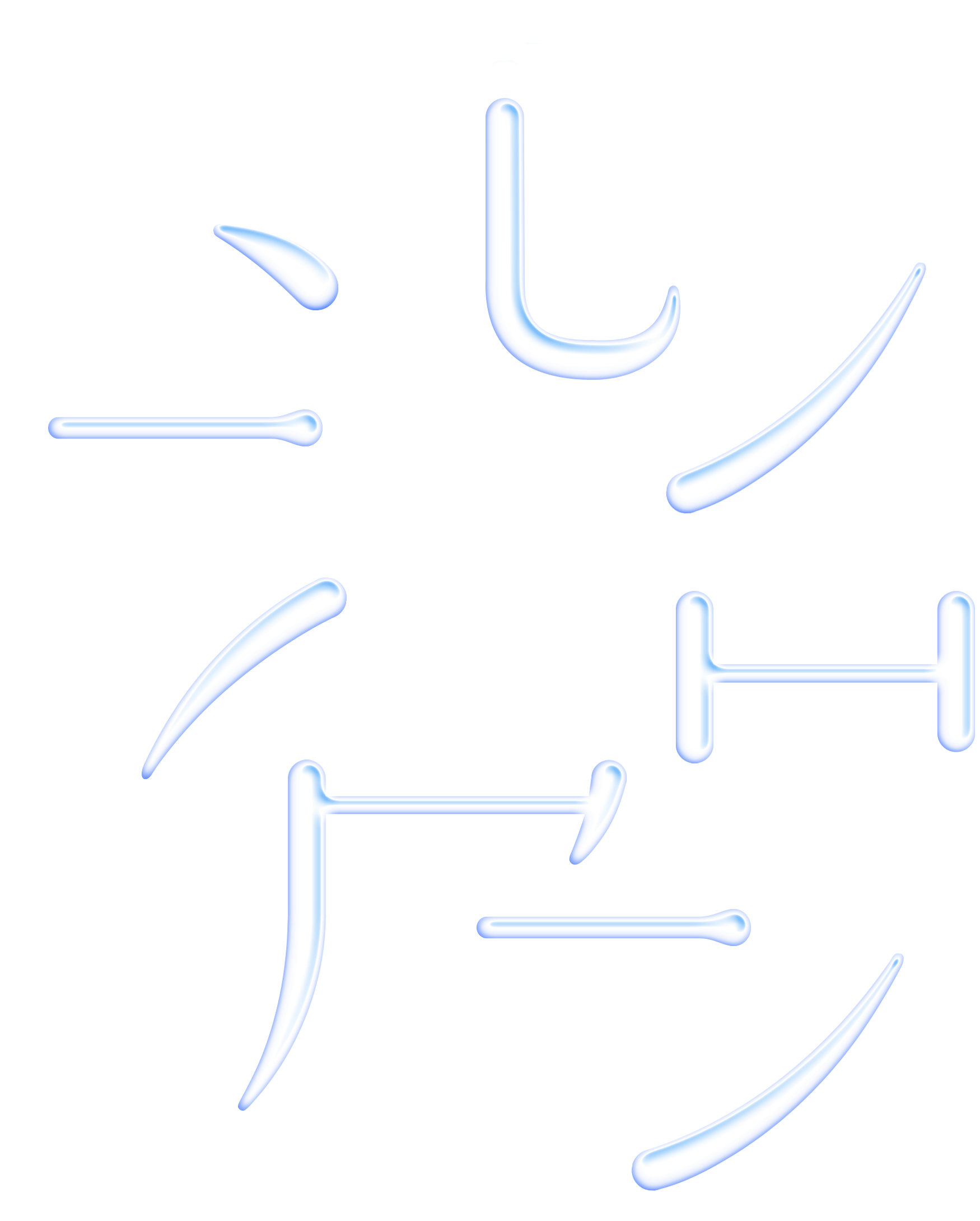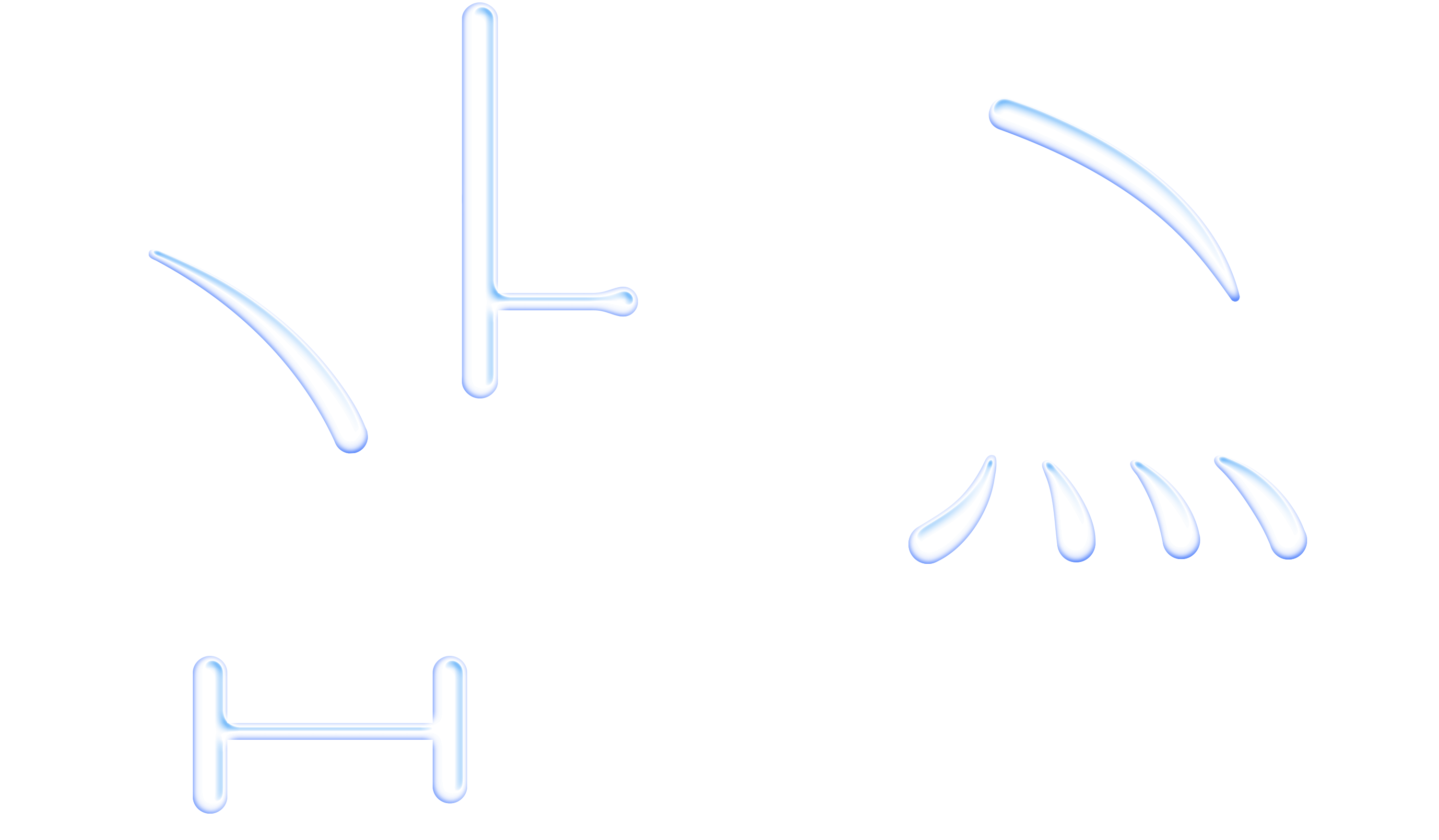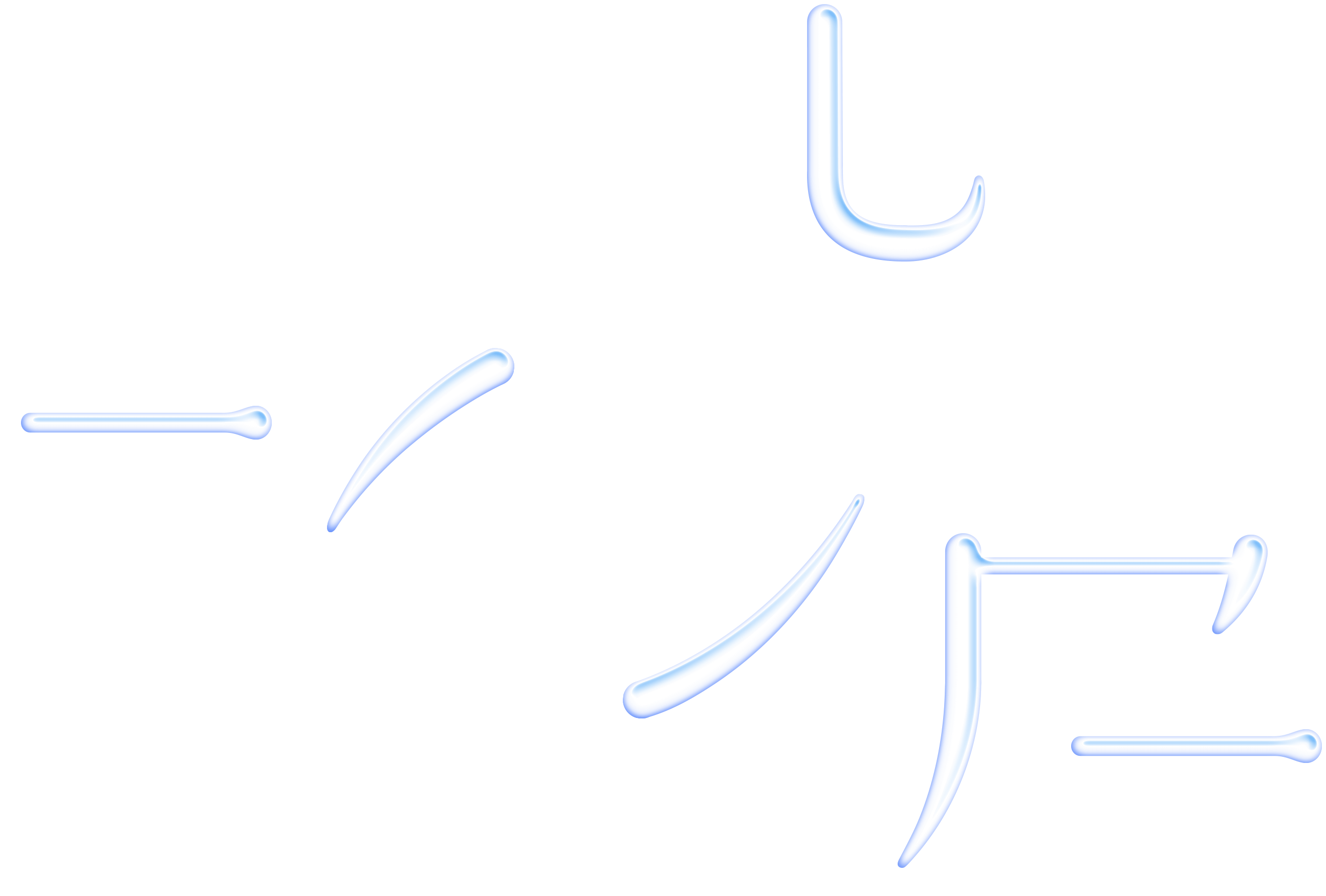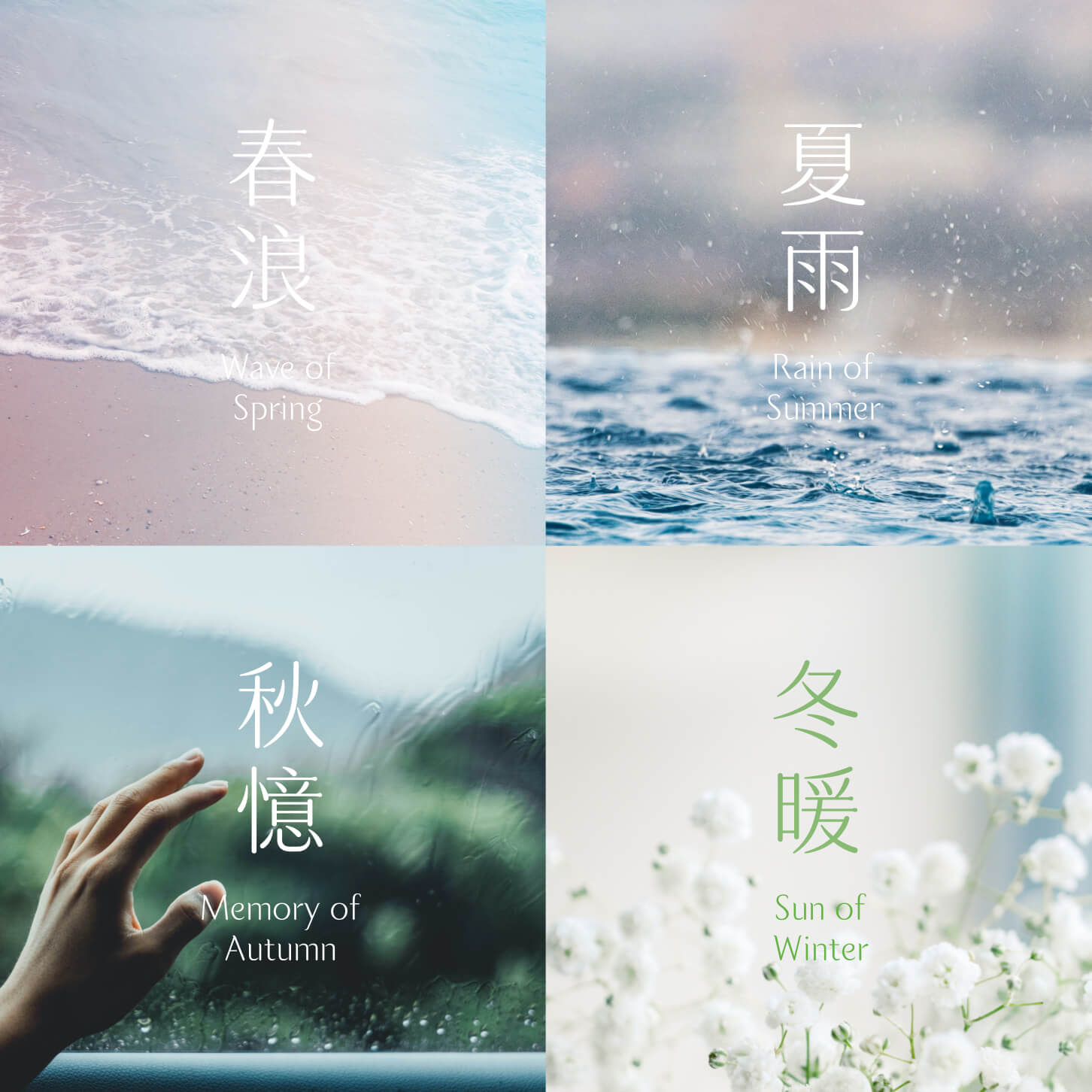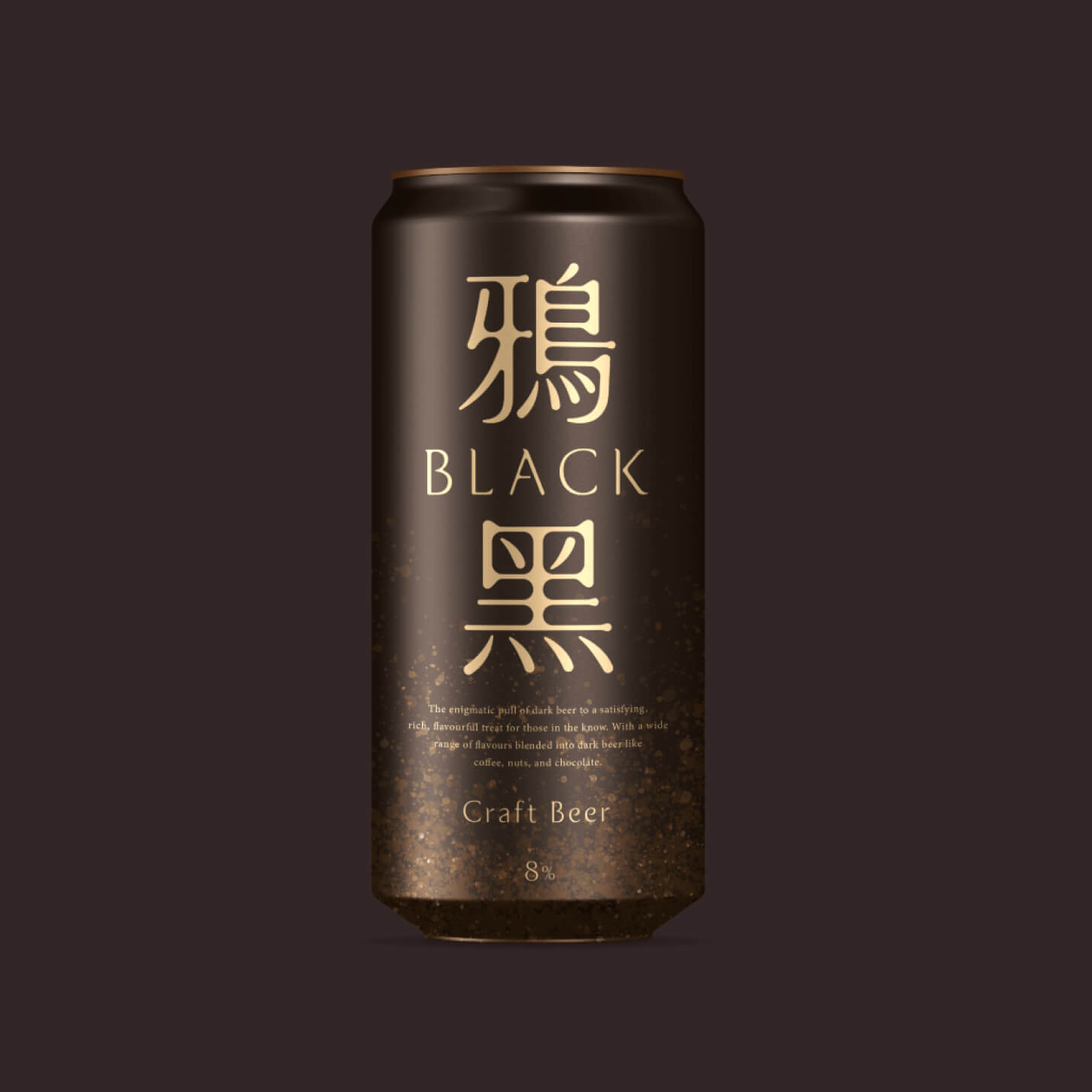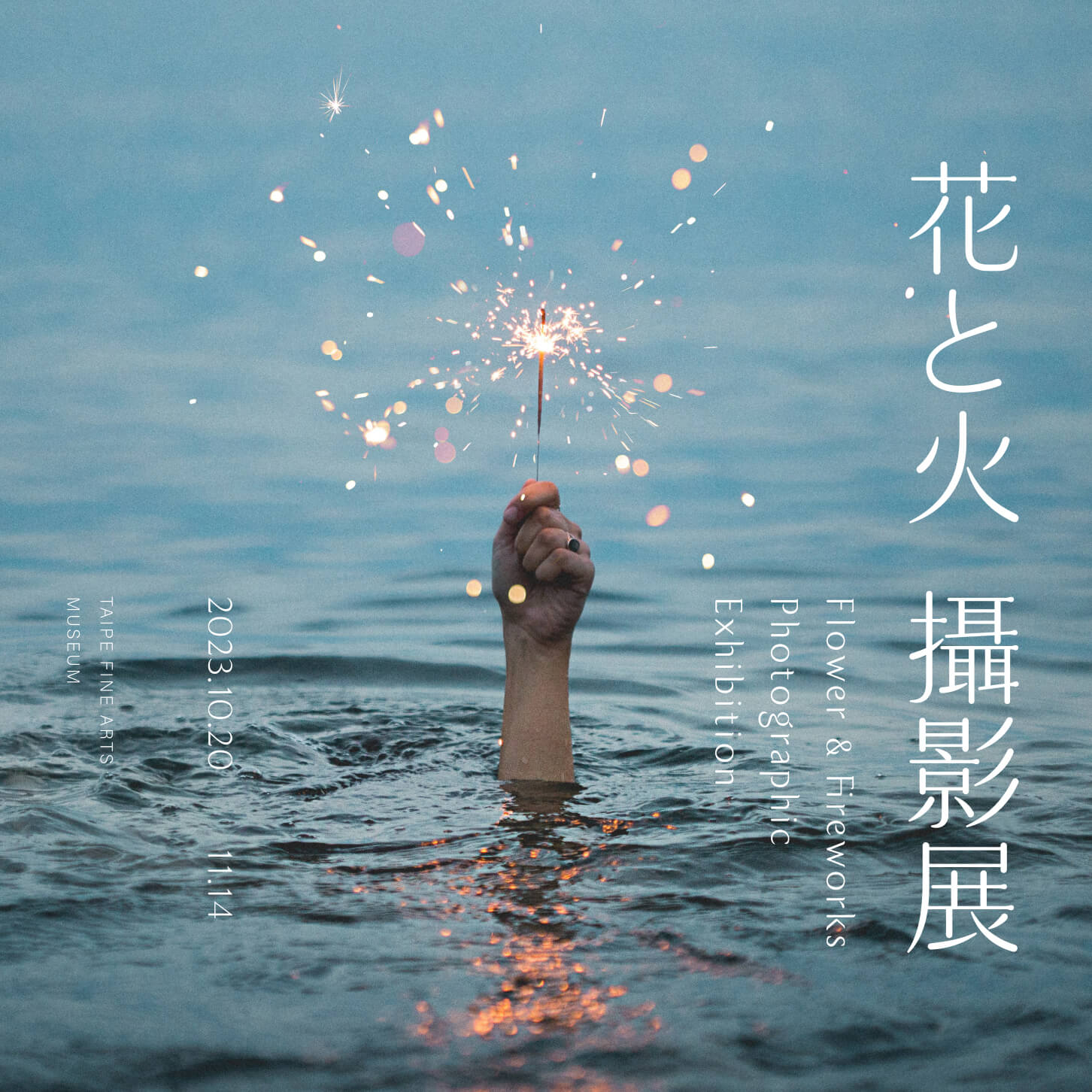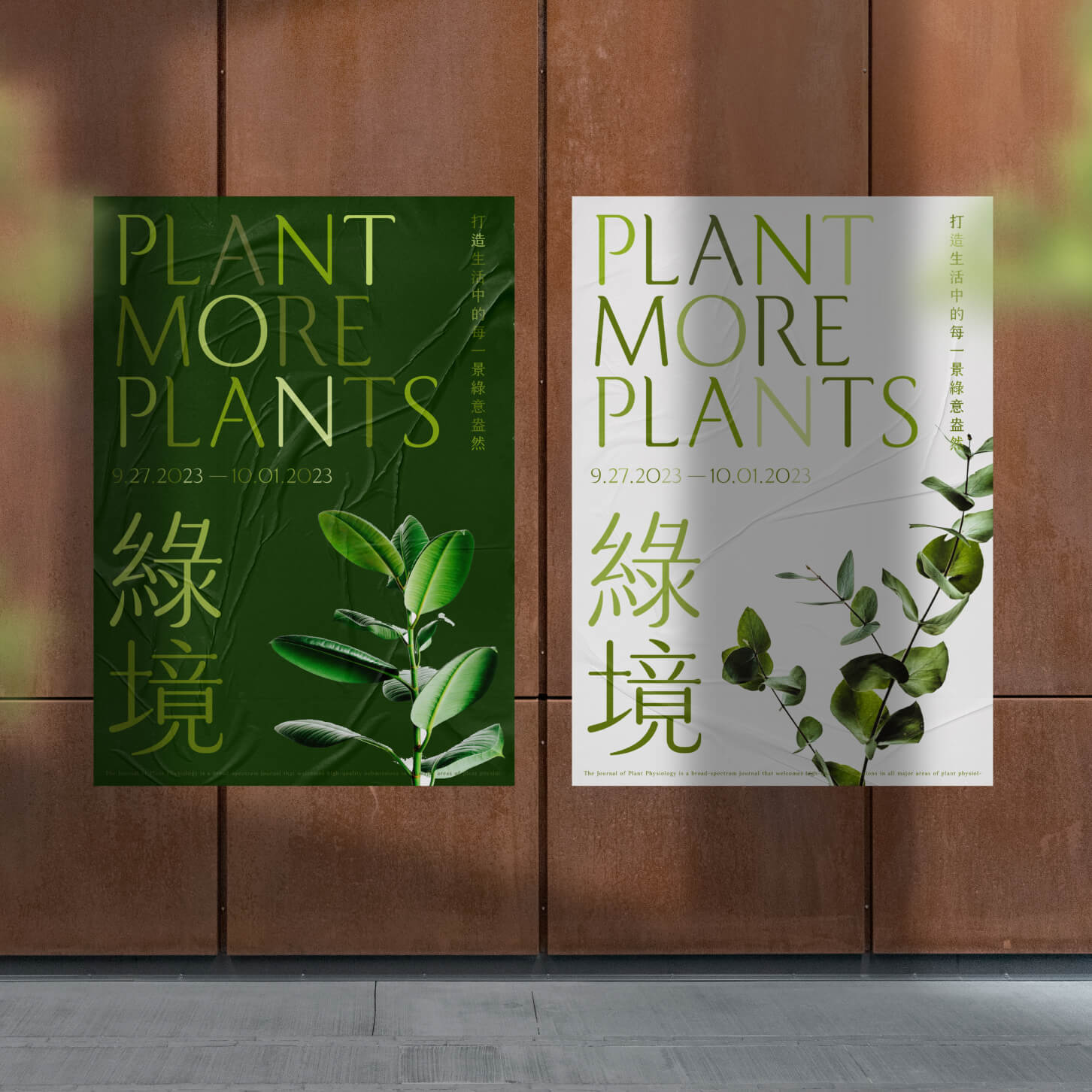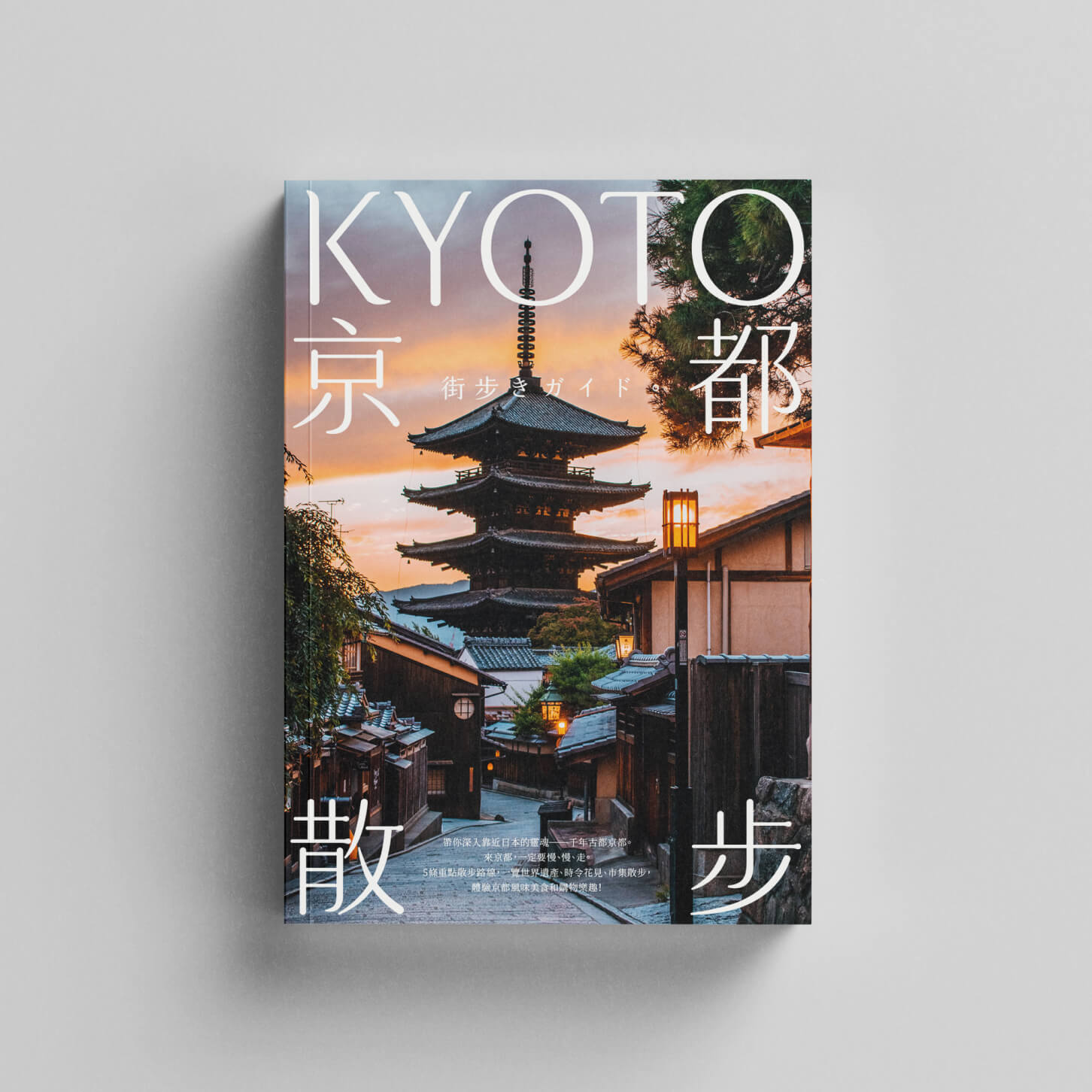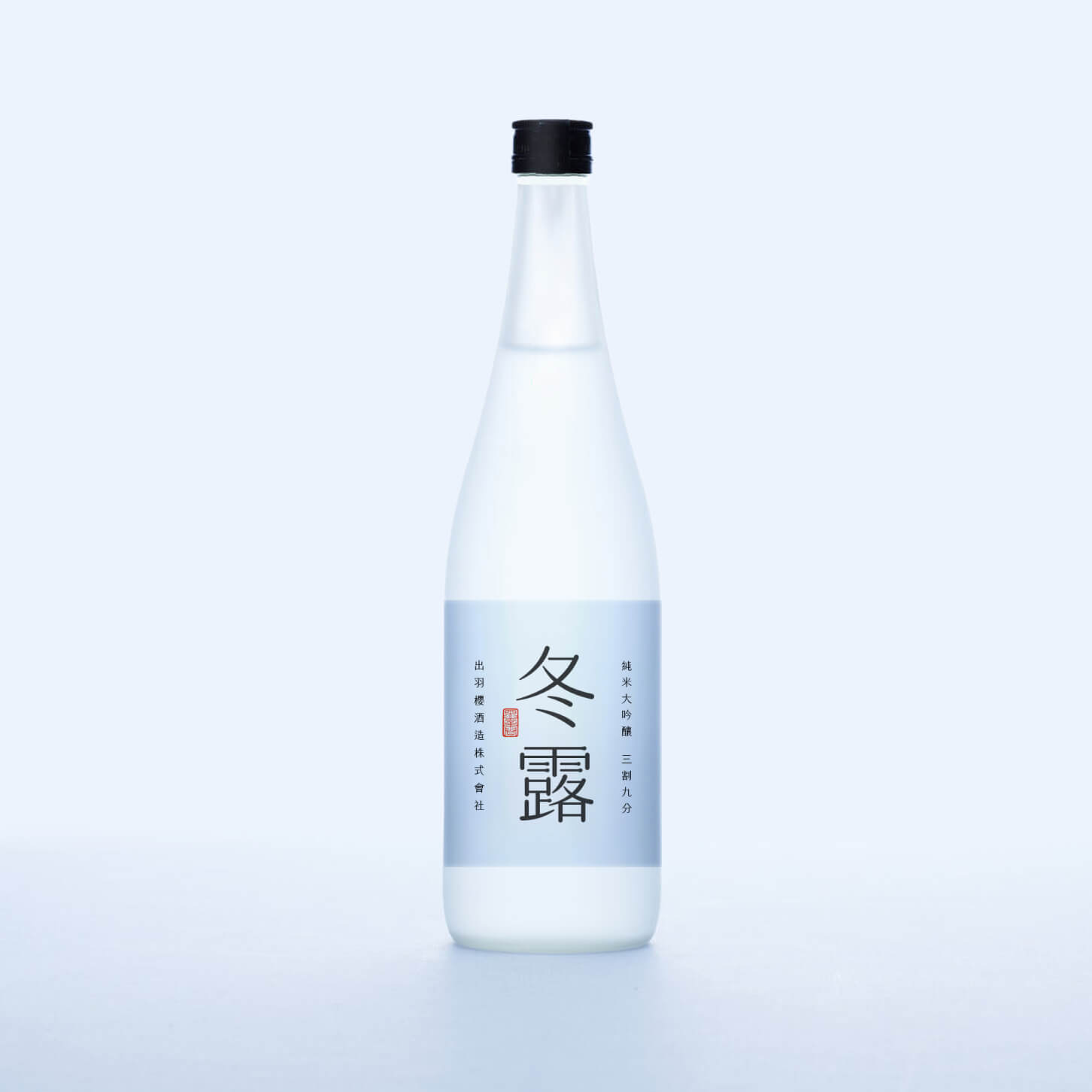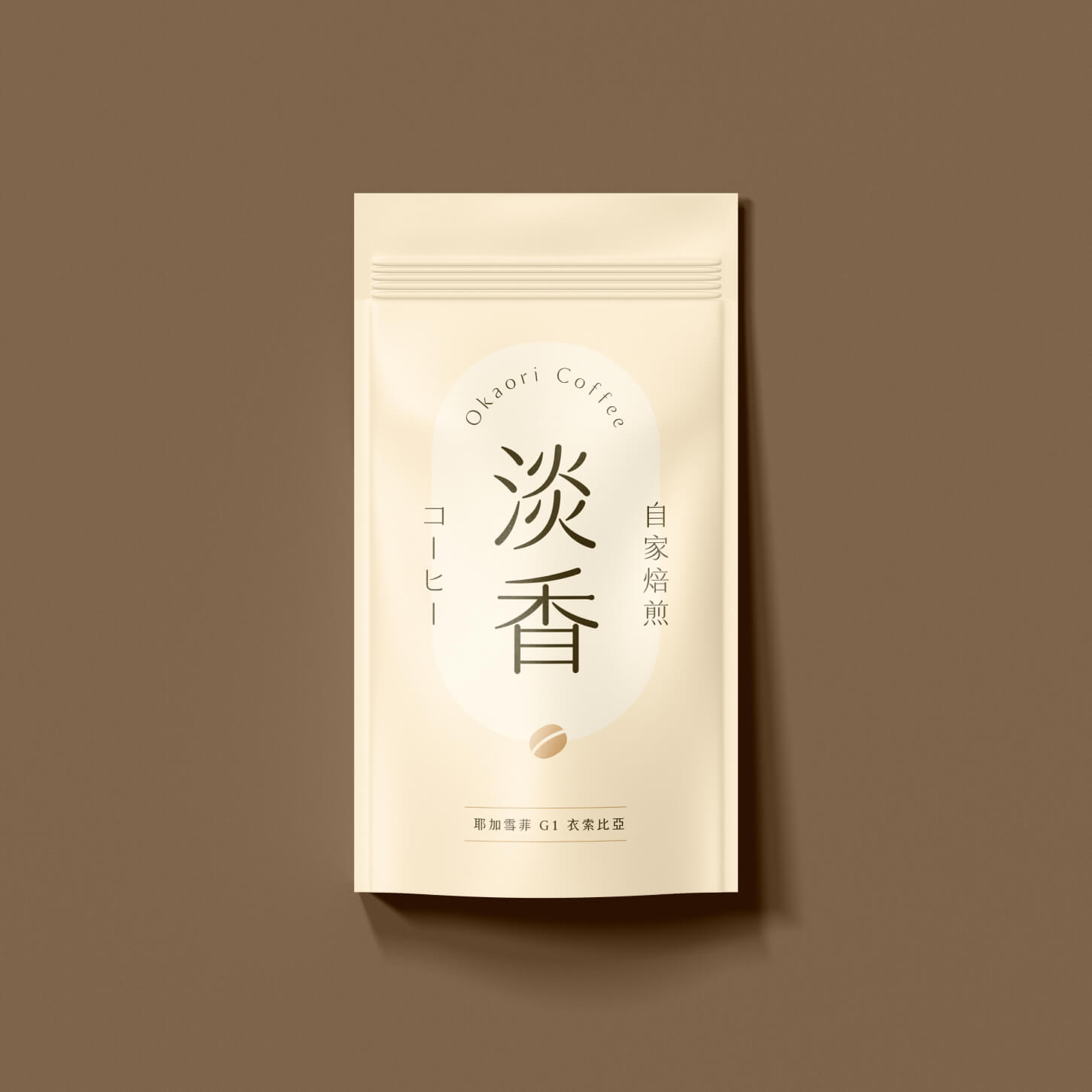
淚體
第一眼,就感受細細情感流動,
在情溢乎辭的時刻,淚體是最恰當的媒介。
不完美的,
不是缺憾 drop
墨跡、斷筆皆為字的缺失。
但不完美或許才是真實的存在。
擁抱遺憾,化為美,於是有了淚體。
自然流露的 淚滴筆型
もりmori
手繪針筆的 積墨痕跡
さんthree
通透舒展的 筆畫間隙
ふくろbag
穩定優雅的 明體架構
ひがしeast
話未說
淚眼
已朦朧
《 淚體 VF 版 》
借助可變式字體技術(Variable Fonts)
讓淚體可調整筆畫交接處的溢墨程度。
讀起來,如淚眼矇矓,
讓文字傳達出更深刻的故事。
淚能說
沒有詞彙
能說的事
淚體的特色是富有感情的細節設計。
適合無話可說、想說但說不出口,
找不到合適的字詞時,
輕輕地溫柔地說。
共感,
超越語言
不只有中文字型必備的
繁體中文、數字、歐文,
淚體亦支援日文假名,以及台語、
客語漢字、羅馬字、白話字與原住民族語。
淚雫で字を描く,
流して詩になる。
淚體日文範例
Teardrops shed in
letters 淚滴畫字,
and there were verses
散落成詩
感性 Emotional / 溫柔 Gentle / 細膩 Delicate
空氣感 Atmospheric / 透明 Transparent
輕盈 Light / 純淨 Pure / 優雅 Graceful
舒服 Comfortable
淚體英文範例
淚體台客語範例